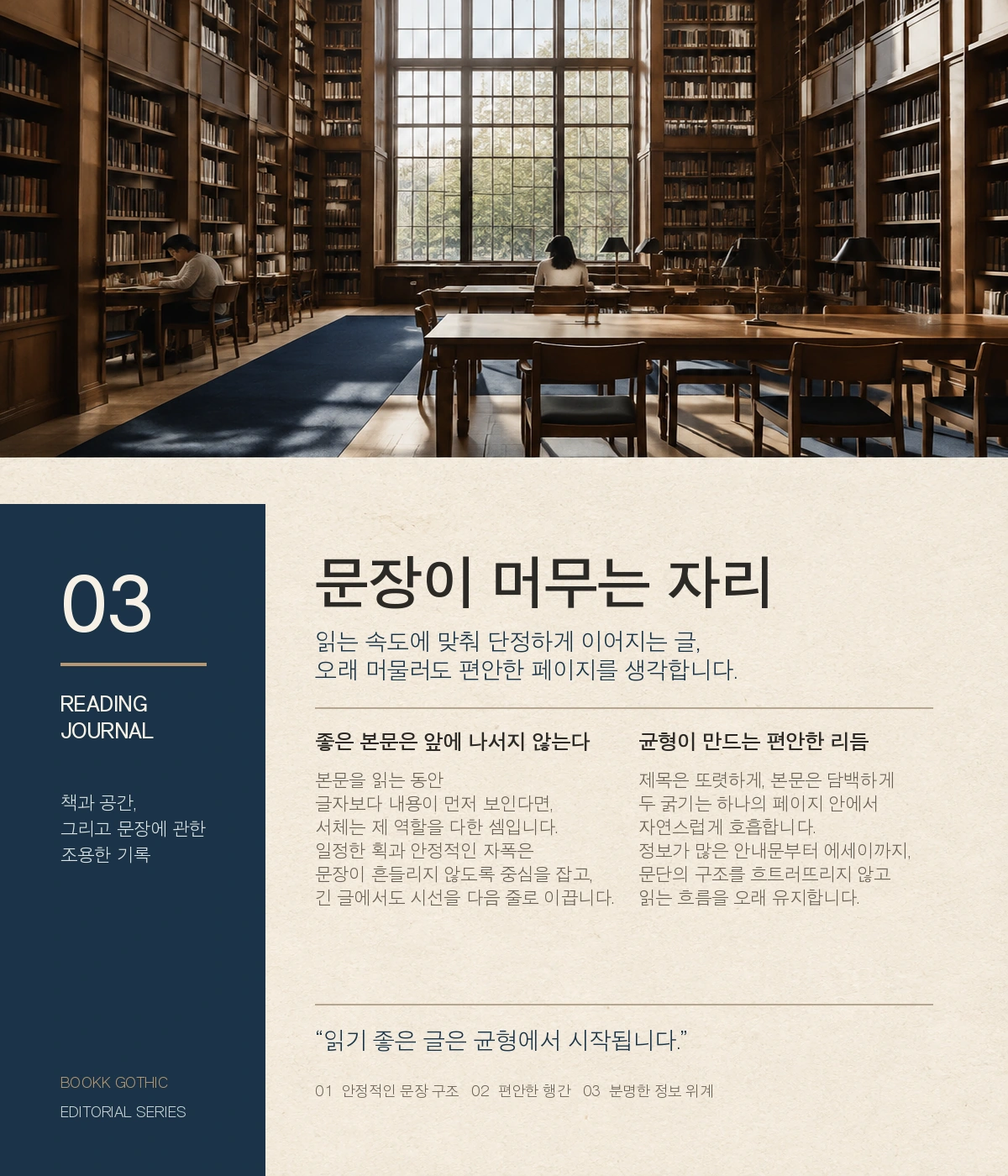
부크크고딕 — 부크크에서 배포하는 무료 폰트입니다. 종이책 본문을 위해 산돌이 그린 서체로, 안정감과 균형에 집중한 부리 없는 본문용 고딕체
자가출판 플랫폼 부크크가 배포하는 서체로 산돌이 제작했습니다. 책을 쓰는 작가와 읽는 독자 모두를 위해 만들었다는 것이 배포처의 설명이고, 종이책 인쇄를 위한 본문용 서체로 소개됩니다.
부크크가 직접 쓴 조형 설명은 따로 공개돼 있지 않습니다. 계열은 부리가 없는 민부리이고, 짝을 이루는 부크크명조와 함께 쓰면 본문과 제목을 나눌 수 있습니다. 자가출판이라는 쓰임이 곧 설계 배경인 셈입니다.
굵기는 Light와 Bold 두 가지입니다. 개인과 기업 모두 무료로 상업적으로 쓸 수 있지만 수정과 편집이 금지되어 배포되는 형태 그대로 써야 합니다. 폰트 파일을 유료로 파는 것도 금지됩니다. 이 서체를 쓴 제작물이 부크크의 홍보에 활용될 수 있다는 조항도 있습니다.